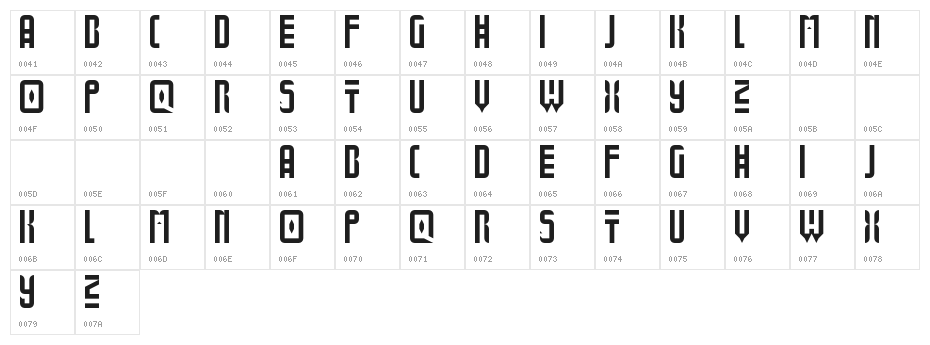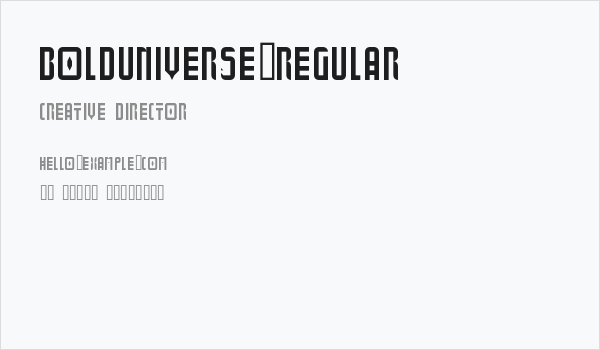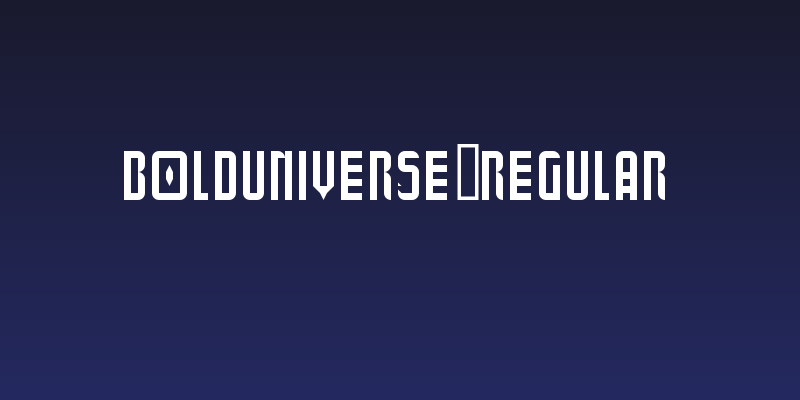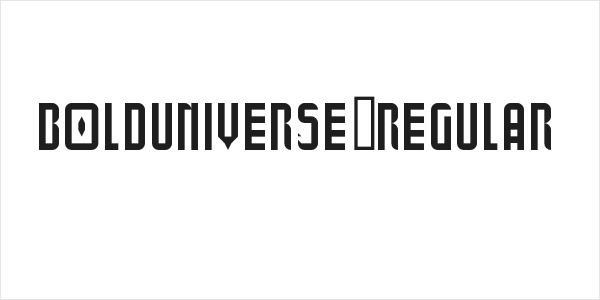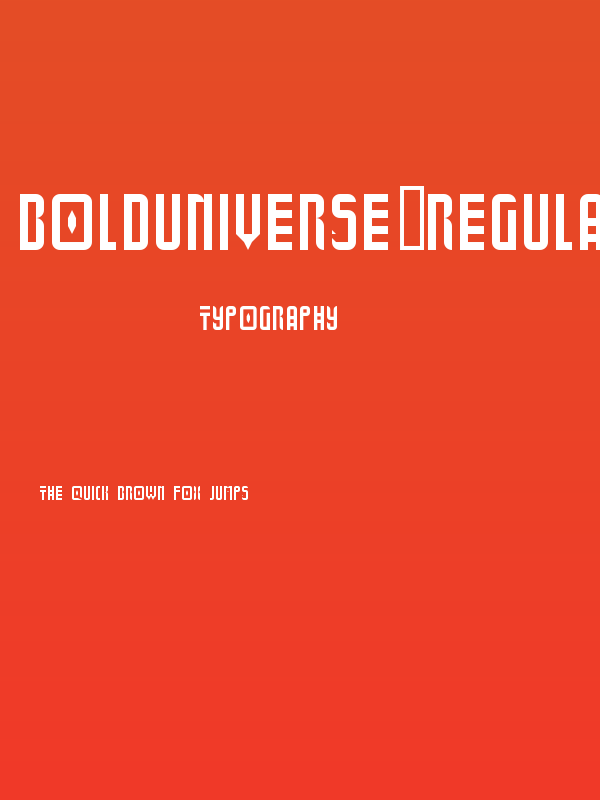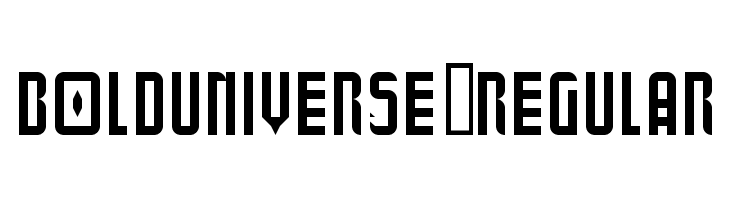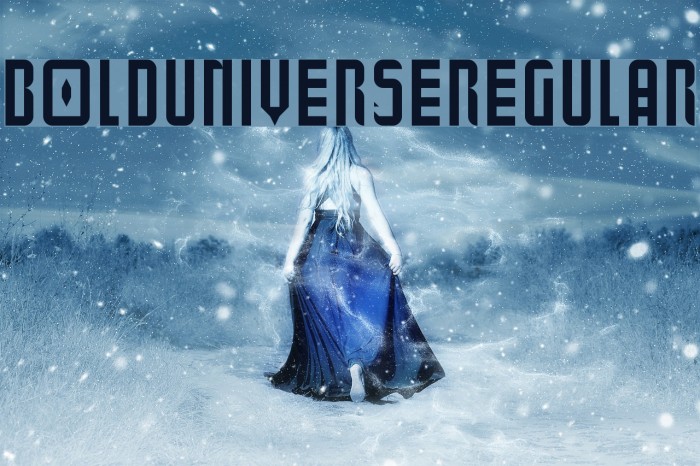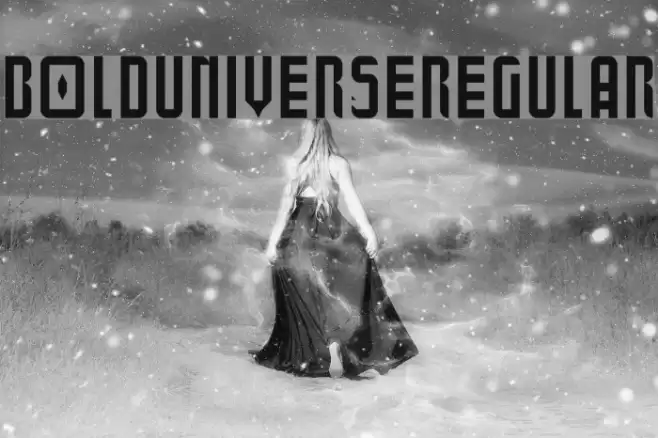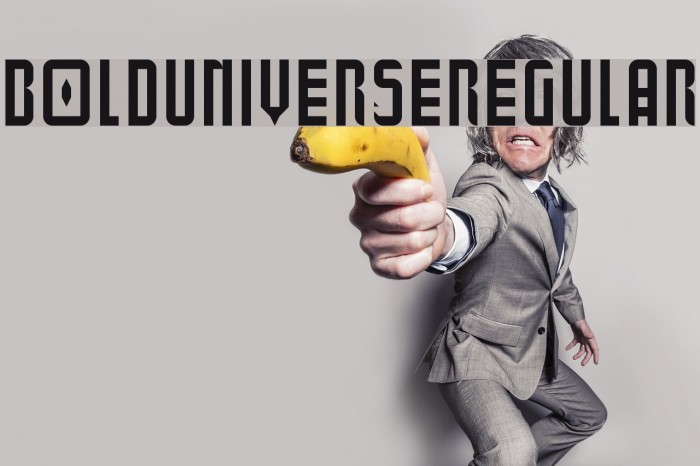
BoldUniverse-Regular Font
✎ Futuristic
| Категория | Futuristic |
| Общий стиль | Futuristic, Industrial |
| Рекомендуемые проекты | This font is perfect for projects that require a strong visual impact, such as posters, logos, branding materials, and signage. Its futuristic and industrial style makes it suitable for tech-related designs or modern art installations. |